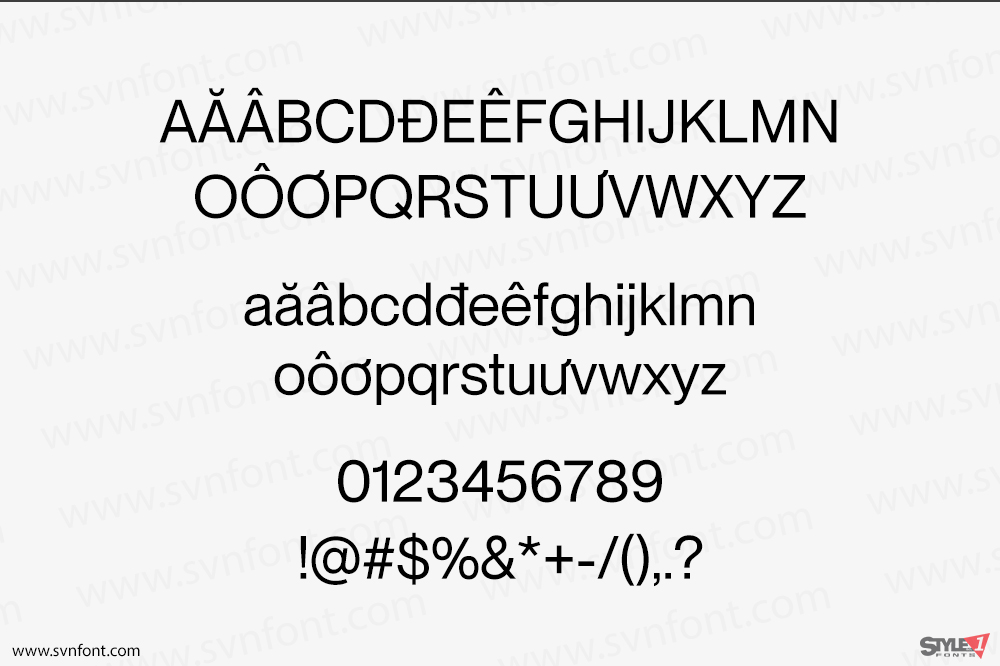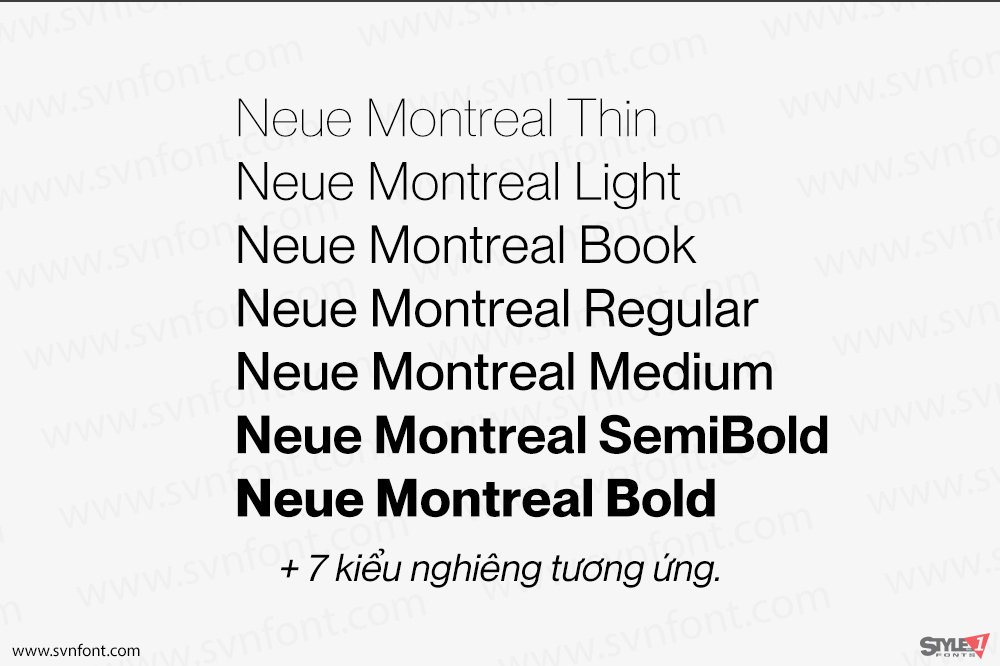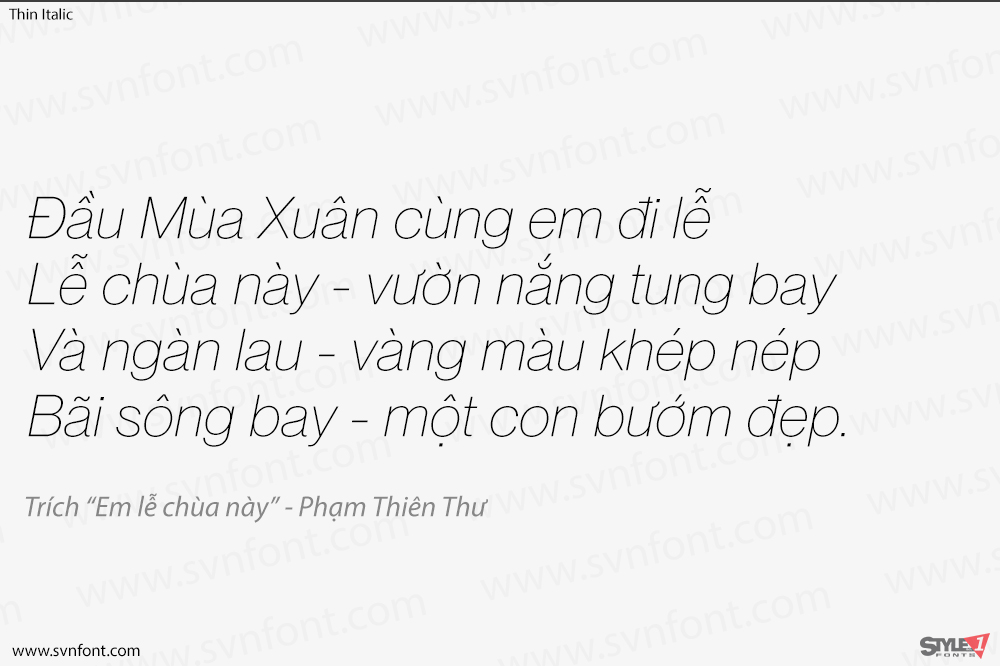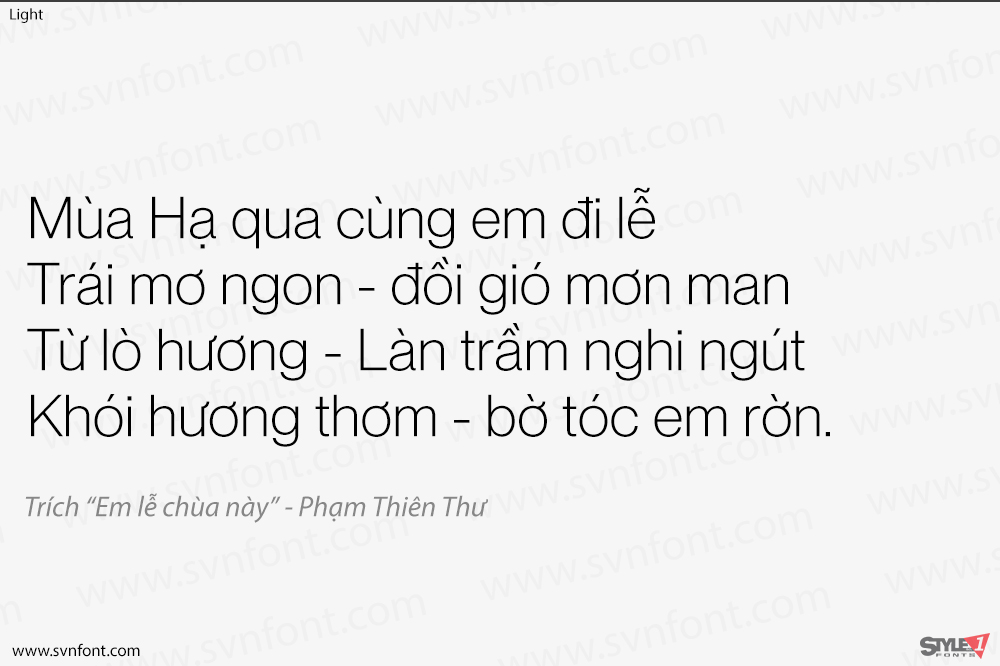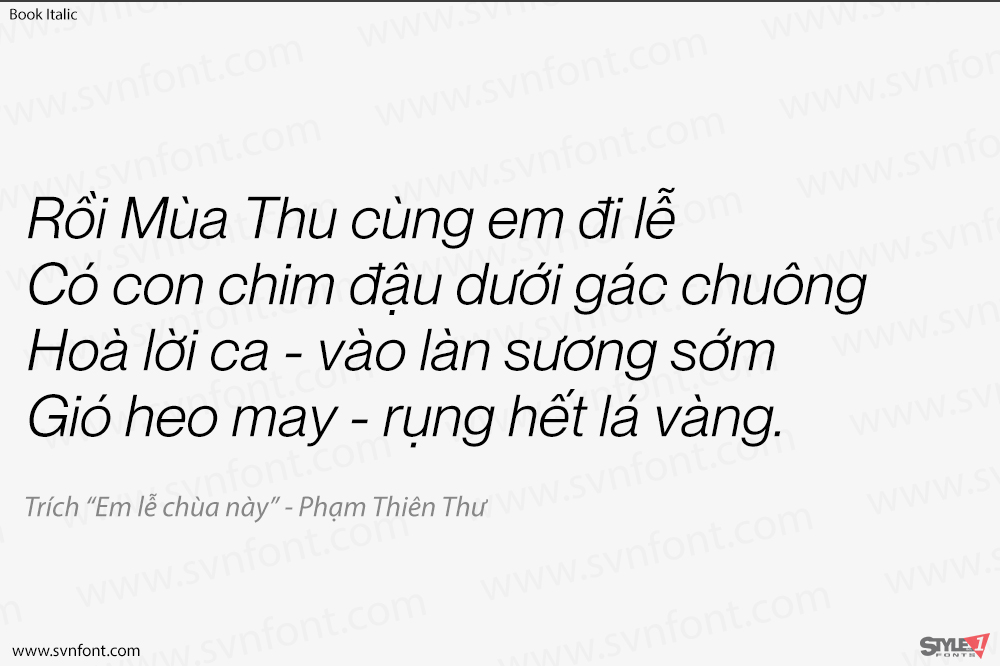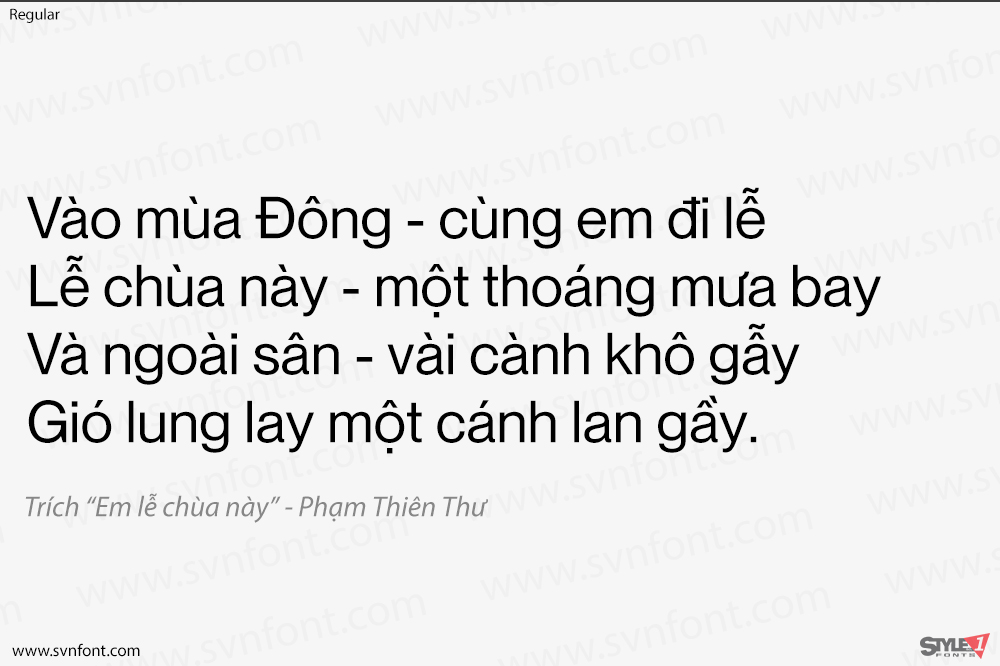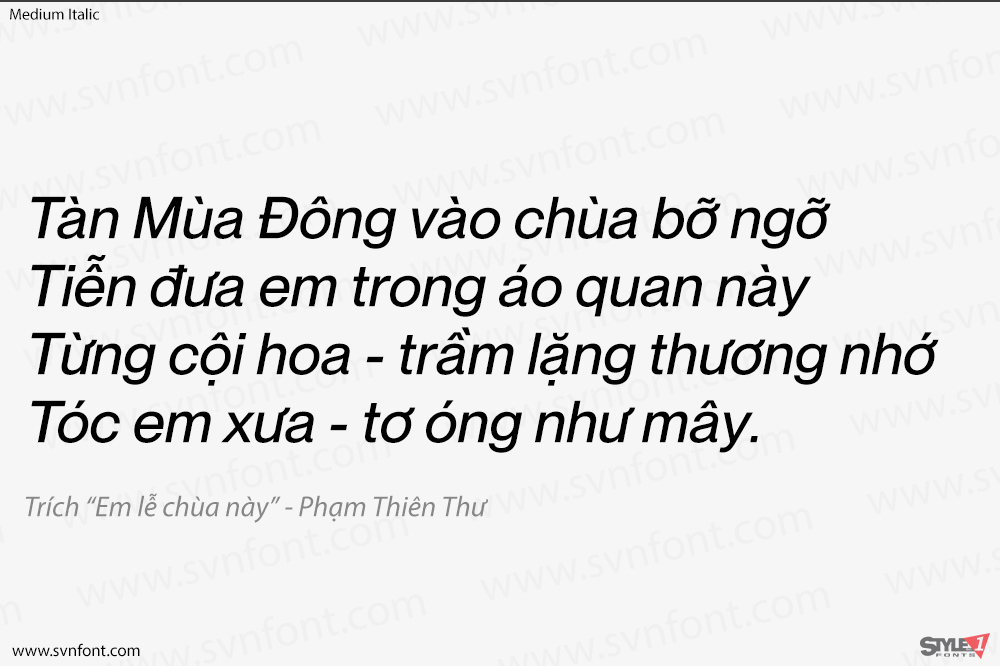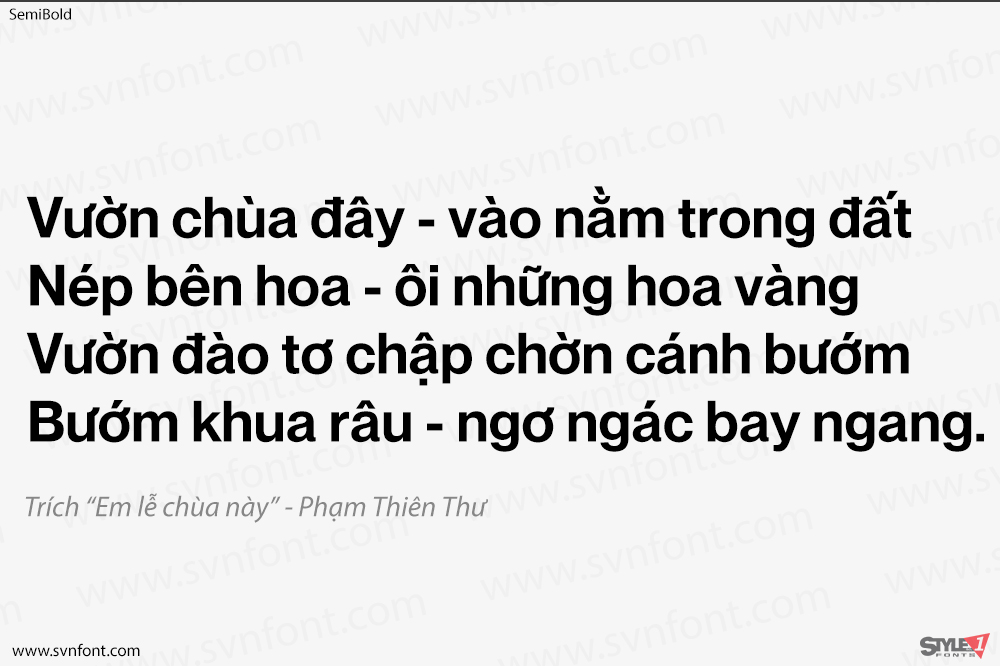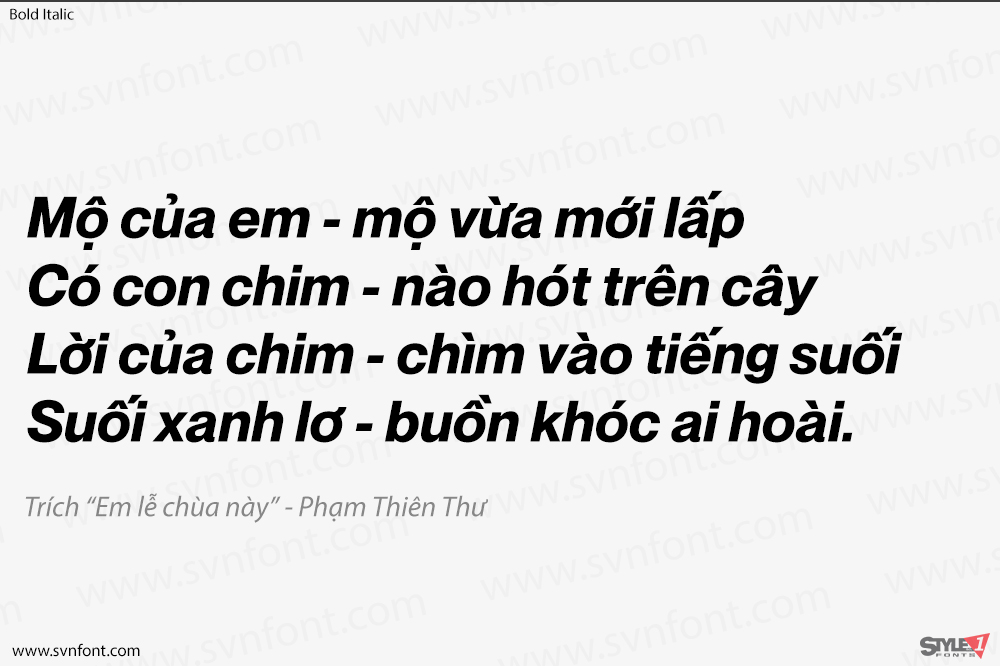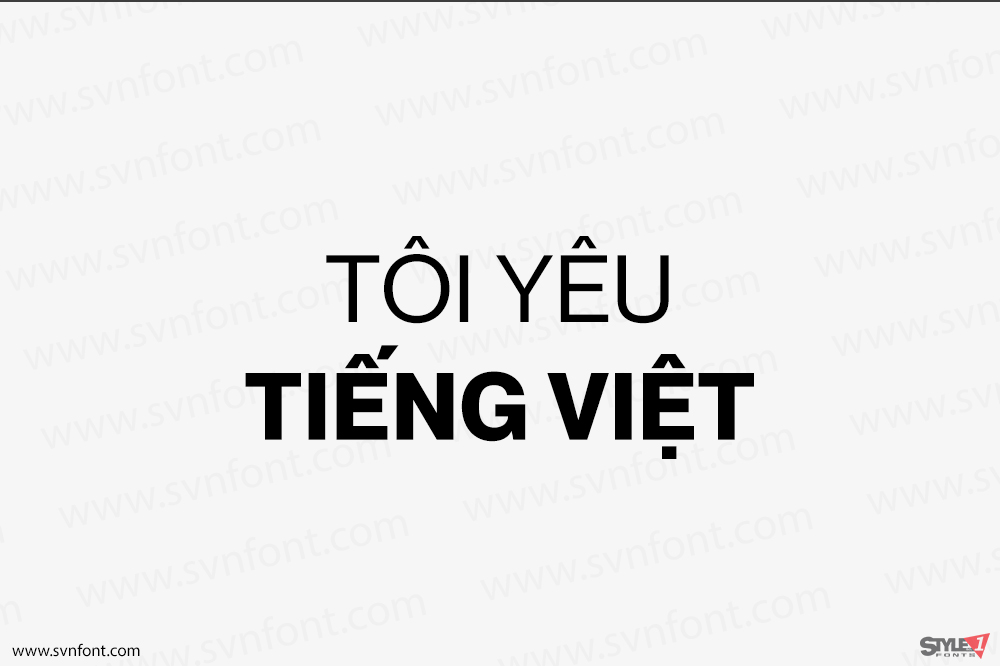
Một phông chữ Grotesque đa năng mang tinh thần của một phông chữ hiển thị ● Hoàn chỉnh với 14 độ dày (7 thẳng đứng, 7 nghiêng) và kerning hơi chặt hơn, bao gồm hỗ trợ Cyrillic. Kiểu chữ này được tạo ra để trở thành phông chữ vô địch tiếp theo của bạn.
Kiểu Sans vượt thời gian này được lấy cảm hứng từ những yếu tố làm nên Neue Montreal – thành phố thiết kế tuyệt vời như ngày nay, từ Expo 67 đến bối cảnh thiết kế đương đại sôi động. Nó đã được nhiều thương hiệu địa phương sử dụng, đáng chú ý nhất là việc tái thương hiệu gần đây của câu lạc bộ bóng đá thành phố Montreal FC.
Nhà thiết kế: Mat Desjardins
Nhà phát hành: Pangram Foundry